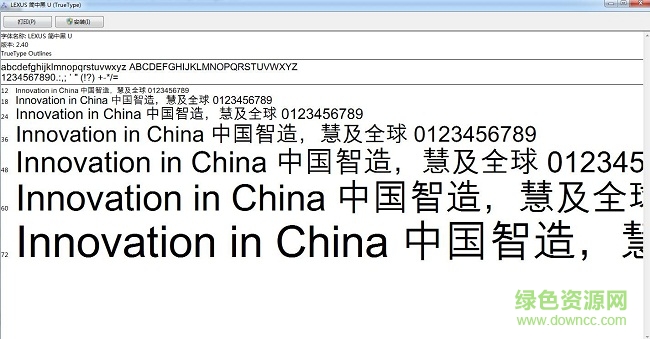
lexus 簡中黑 u medium
lexus 簡中黑 u medium字體又叫雷克薩斯簡中黑,該字體線條醒目,氣質(zhì)堅毅,十分干練,常常用在文章的標題、海報標語等方面,歡迎大家免費下載!
黑體字體基本特點
1. 筆畫粗;
2. 筆畫端口方直。
lexus 簡中黑 u medium
黑體應(yīng)用要求
黑體的各個筆劃寬度雖是大致相等,但不是絕對的,在處理上不能強求一律,否則筆劃多的字必然擁塞寫不下,筆劃少的則顯得空,所以應(yīng)在長與短、橫與豎、筆劃粗與細之間,作適當?shù)恼{(diào)整,達到整體上的均勻諧調(diào)。